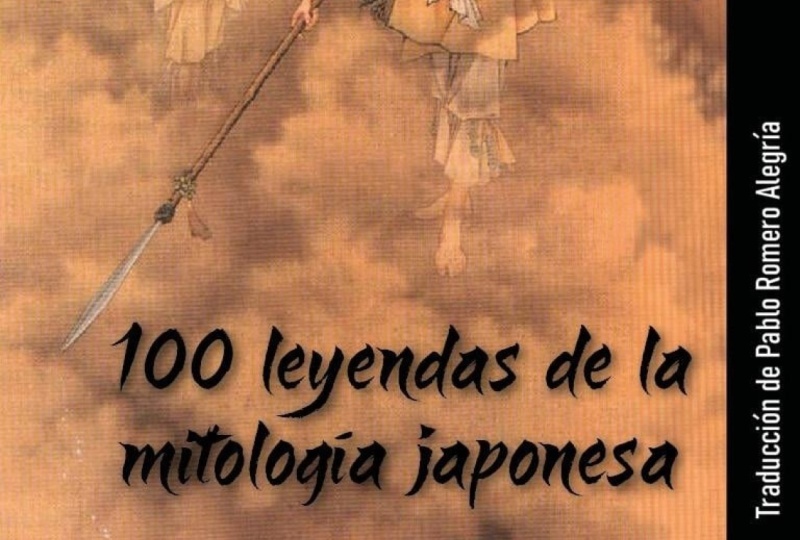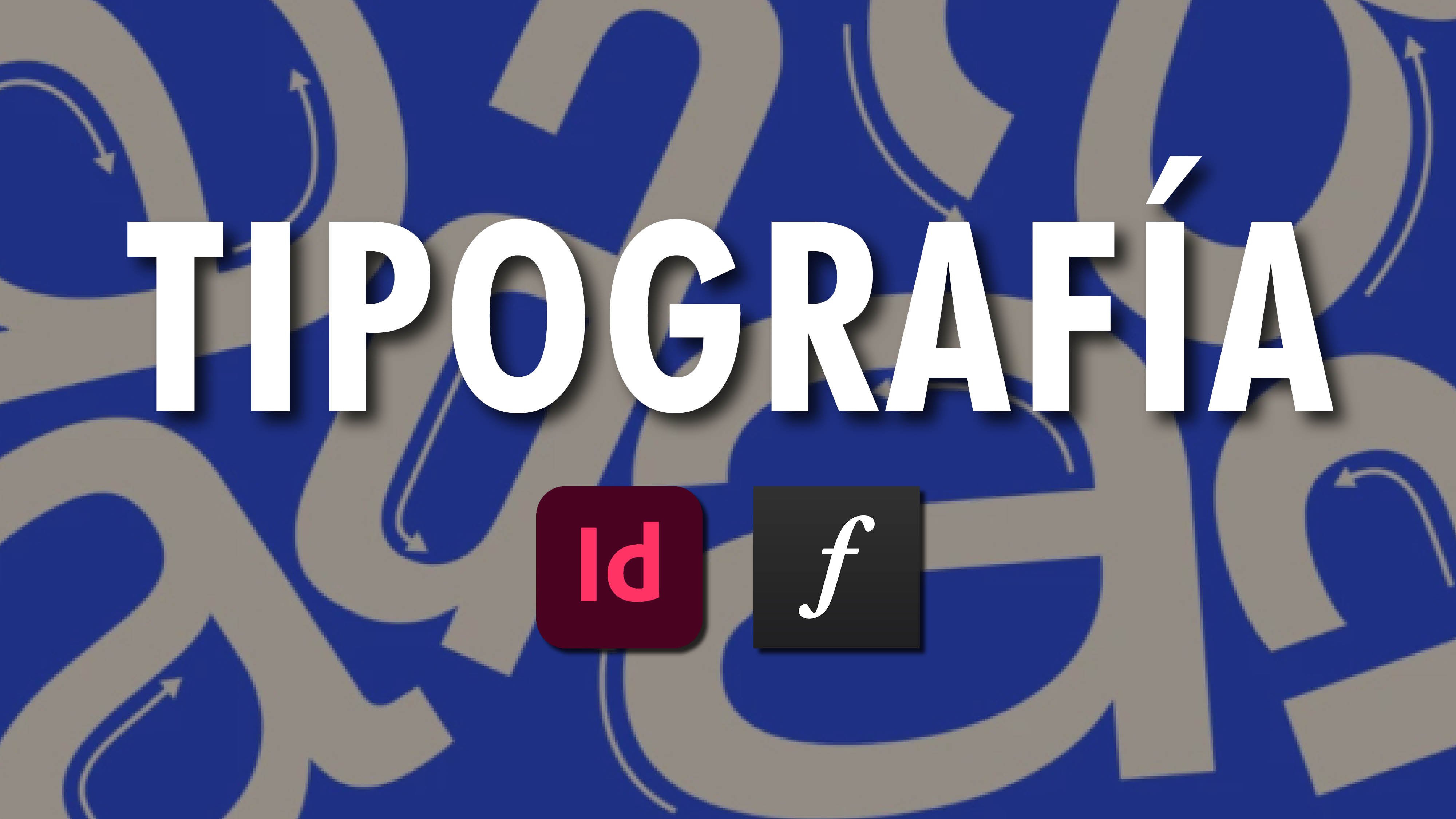
Tipografía: historía, técnica y creatividad en InDesign
Conceptos generales sobre tipografía
Historia de la escritura a mano
De Góticas a Romanas
Tipografías de transición
Didonas o Romanas modernas
La Revolución Industrial
Grotescas o San Serifs
Estilo Suizo o Estilo Internacional
Clasificación tipográfica Vox-Typl
Anatomía del tipo
Ejercicio cubiertas (Primera parte)
Menú tipografías en InDesign
Aplicar texturas, usar tipografías como máscaras y nuevas herramientas de IA
Aprendiendo a usar Adobe Fonts
IA en Indesign. Sacar una tipografía de una imagen
Ejercicio final. Cubiertas (Segunda parte)
"Tipografía: historia, técnica y creatividad con InDesign" es un recorrido completo por el arte de las letras, desde su evolución a lo largo de los siglos hasta su aplicación profesional en el diseño editorial actual. Aprenderás los fundamentos históricos que han dado forma a las tipografías modernas y cómo aplicar ese conocimiento para tomar decisiones tipográficas más informadas y creativas.
A lo largo del curso, exploraremos los estilos clásicos y contemporáneos, los movimientos tipográficos más influyentes y la anatomía de las letras. Luego, llevaremos esa teoría a la práctica utilizando Adobe InDesign, donde aprenderás a trabajar con estilos de texto, jerarquías visuales, espaciado, alineación y composición tipográfica para crear diseños funcionales y estéticamente impactantes.
Ideal para diseñadores gráficos, editores, comunicadores visuales y cualquier persona interesada en dominar el lenguaje de la tipografía con herramientas profesionales.
¿Qué aprenderás?
Historia de la escritura a mano. Desde los egipcios al Renacimiento.
La historia de la tipografía: desde la imprenta de Gutenberg hasta las fuentes digitales contemporáneas.
El papel de la tipografía en el arte, el diseño gráfico y la comunicación visual.
Anatomía de la fuente: términos técnicos y cómo influyen en la legibilidad y el estilo.
Clasificación tipográfica: serif, sans serif, script, display y más.
Principios de composición tipográfica: jerarquía visual, ritmo, alineación, interletrado y espaciado.
Aplicación práctica en Adobe InDesign:
Configuración de estilos y uso del menú tipográfico
Uso de herramientas tipográficas de IA en Indesign
Diseño de piezas editoriales (revistas, libros, folletos, etc.)
Proyecto Final
Encontrar la tipografía adecuada para cada uno de nuestros proyectos muchas veces es la tarea más complicada y la que va a resultar clave para que el proyecto funcione o fracase a nivel gráfico. Gracias a este curso obtendrás el conocimiento y la herramientas necesarias para convertirte en un experto en el arte tipográfico y, no sólo elevar tus proyectos a otro nivel, sino disfrutar en el camino.
Hola a tod@s,
Mi nombre es Manuel Pallarés. Soy arquitecto por la universidad de Alcalá de Henares y la Sapienza de Roma. Mi actividad profesional ha estado ligada tanto a proyectos creativos de diferente índole (diseño editorial, diseño gráfico, paisajismo, arquitectura...), pero siempre he tenido un pie en la enseñanza.
He trabajado como docente en la universidad Superior de Diseño de Valladolid (ESI). También a día de hoy trabajo como profesor en la Escuela Artes Creativas de Madrid e imparto cursos en el espacio cultural de La casa Encendida, en Madrid
La verdad es que me encanta enseñar! Supone una gran satisfacción transmitir tus cono... Vollständiges Profil ansehen
Praxisnahes Kursprojekt
En el proyecto final de curso os propondré 5 cubiertas de libros diseñados por mi previamente en donde tendréis que aplicar las tipografías para los títulos, subtítulos y el nombre del autor.
Cada cubierta obedecerá a un estilo diferente, por lo que tendréis que aplicar todo lo aprendido durante el curso para realizar un diseño tipográfico en armonía con las ilustraciones y el tema propuesto en cada una de las cubiertas.
Una vez finalizado vuestro trabajo podréis ver mis soluciones para contrastar lo resultados.